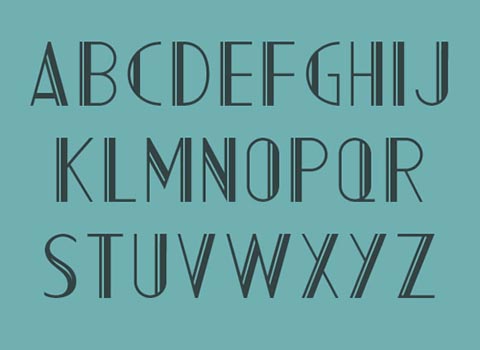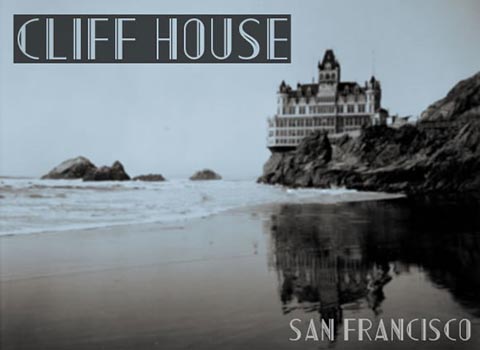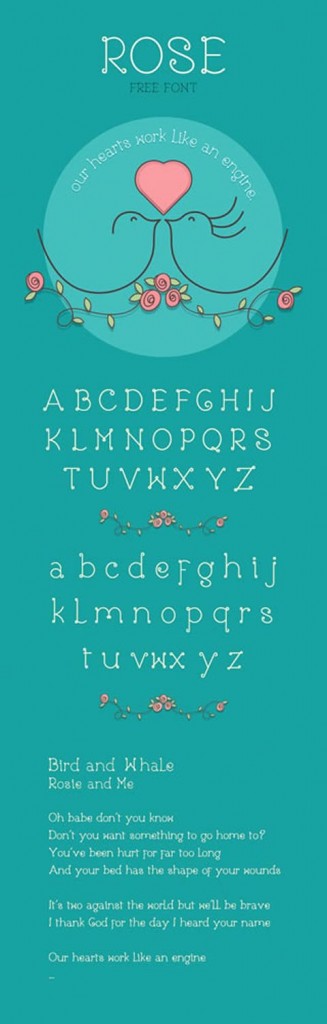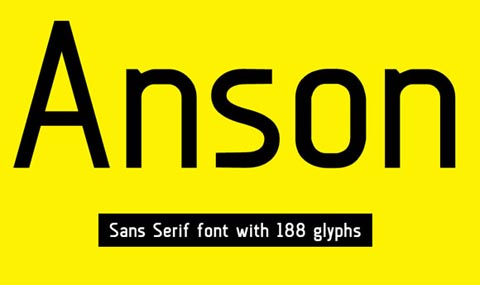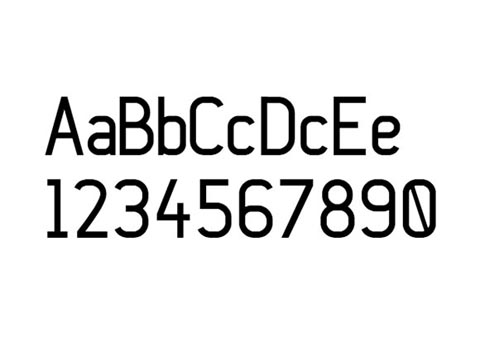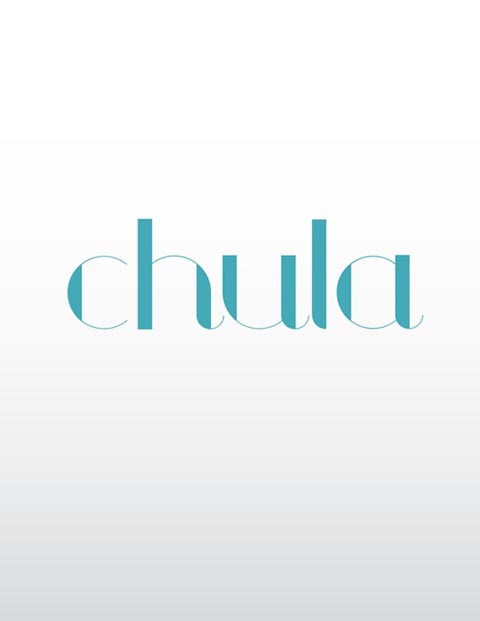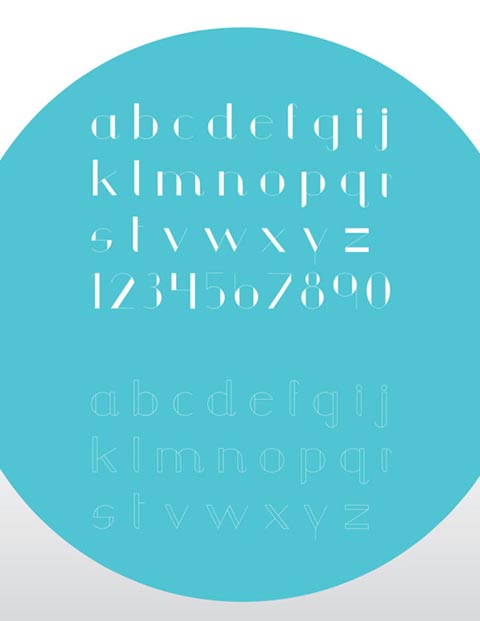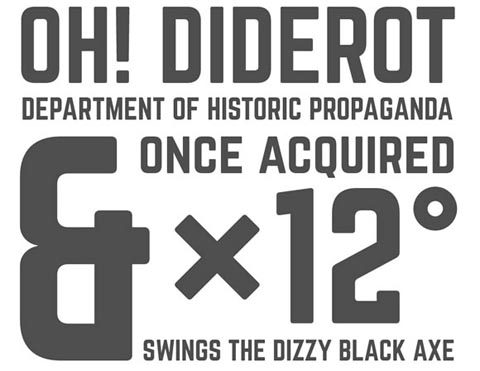
9款時(shí)尚英文字體打包
9款非常時(shí)尚的英文字體是著名的wdl設(shè)計(jì)的,免費(fèi)字體一直以來(lái)都是wdl博客是主推的資源之一,目的是為了幫助設(shè)計(jì)師搜集當(dāng)下最優(yōu)秀的字體資源,提高設(shè)計(jì)效率。這次發(fā)布的9款免費(fèi)英文字體,時(shí)尚、創(chuàng)意和美麗,希望大家喜歡,enjoy!
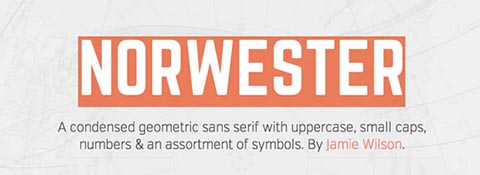
norwester
AC Mountain
Rose
Anson
Chula
Norwester
Kenzo
Franks
PEYO Regular
Plethora 1984